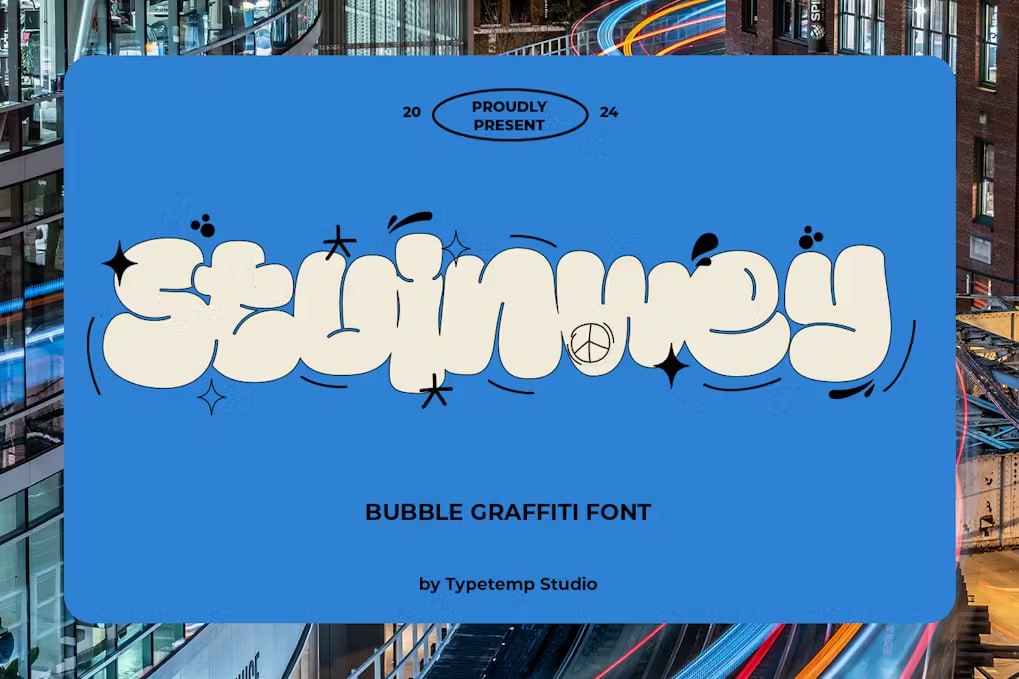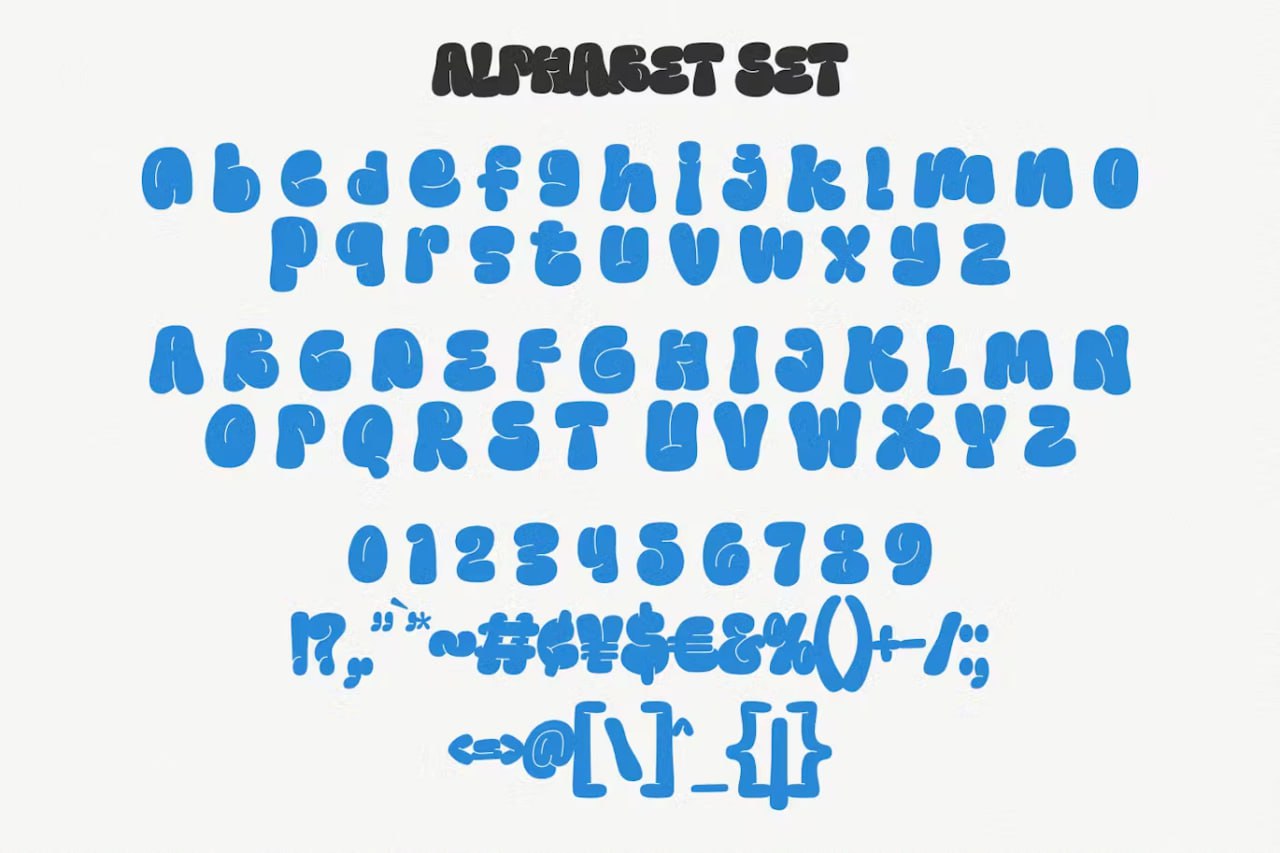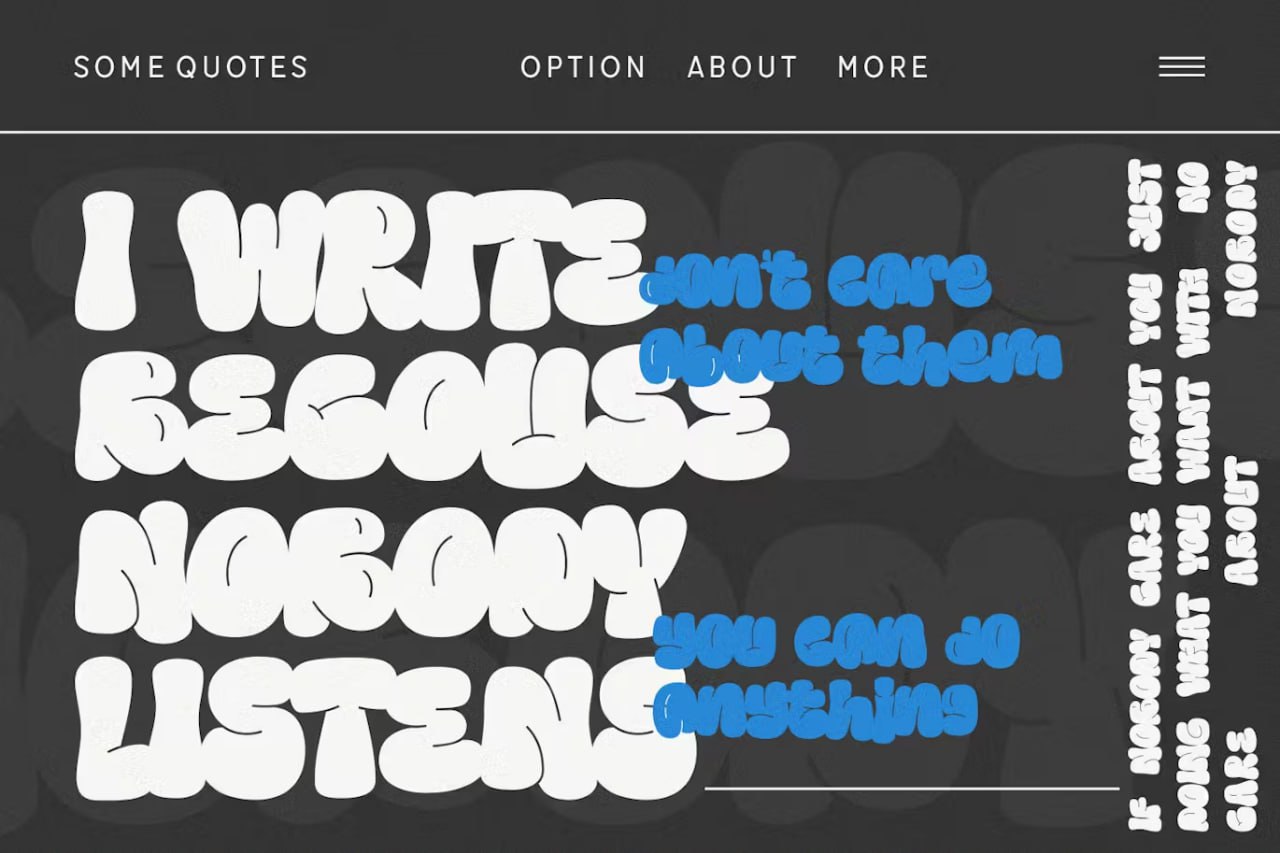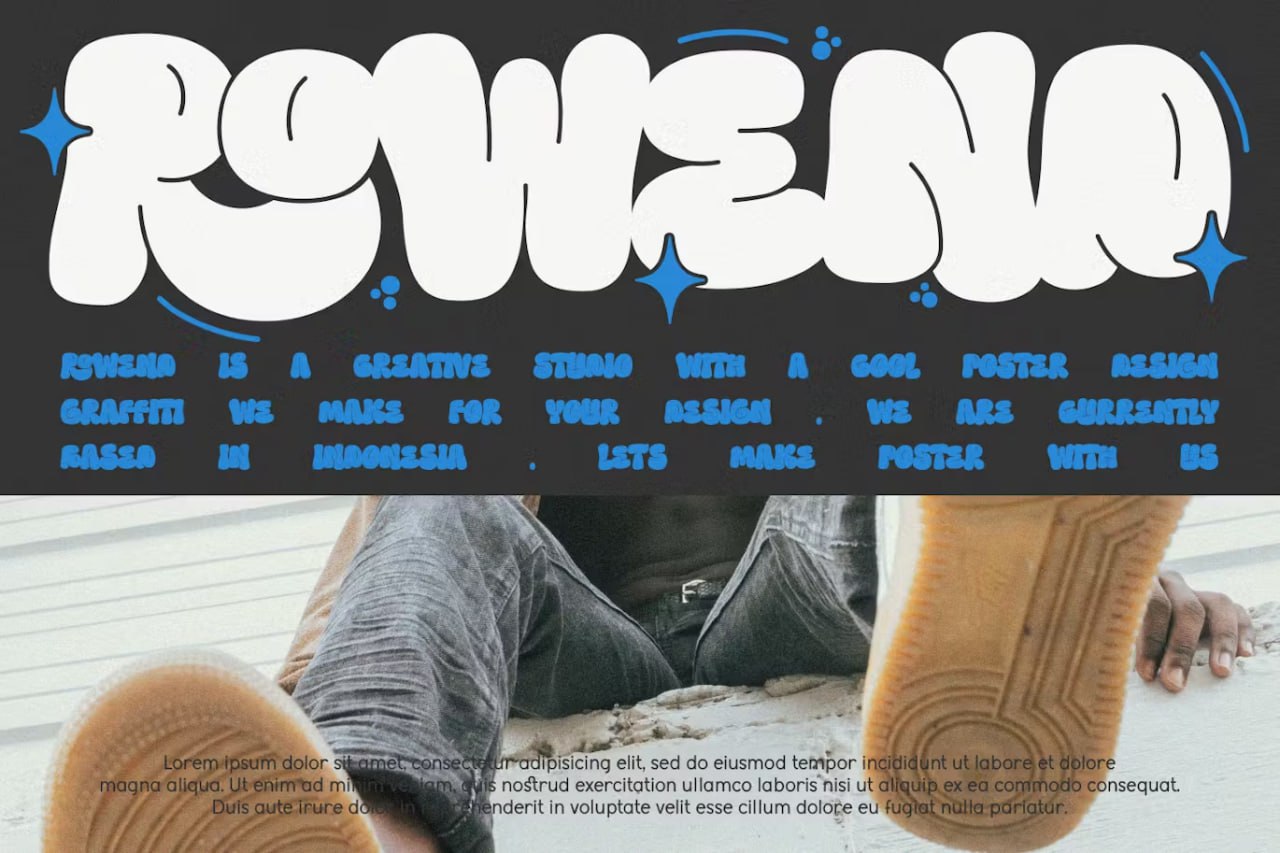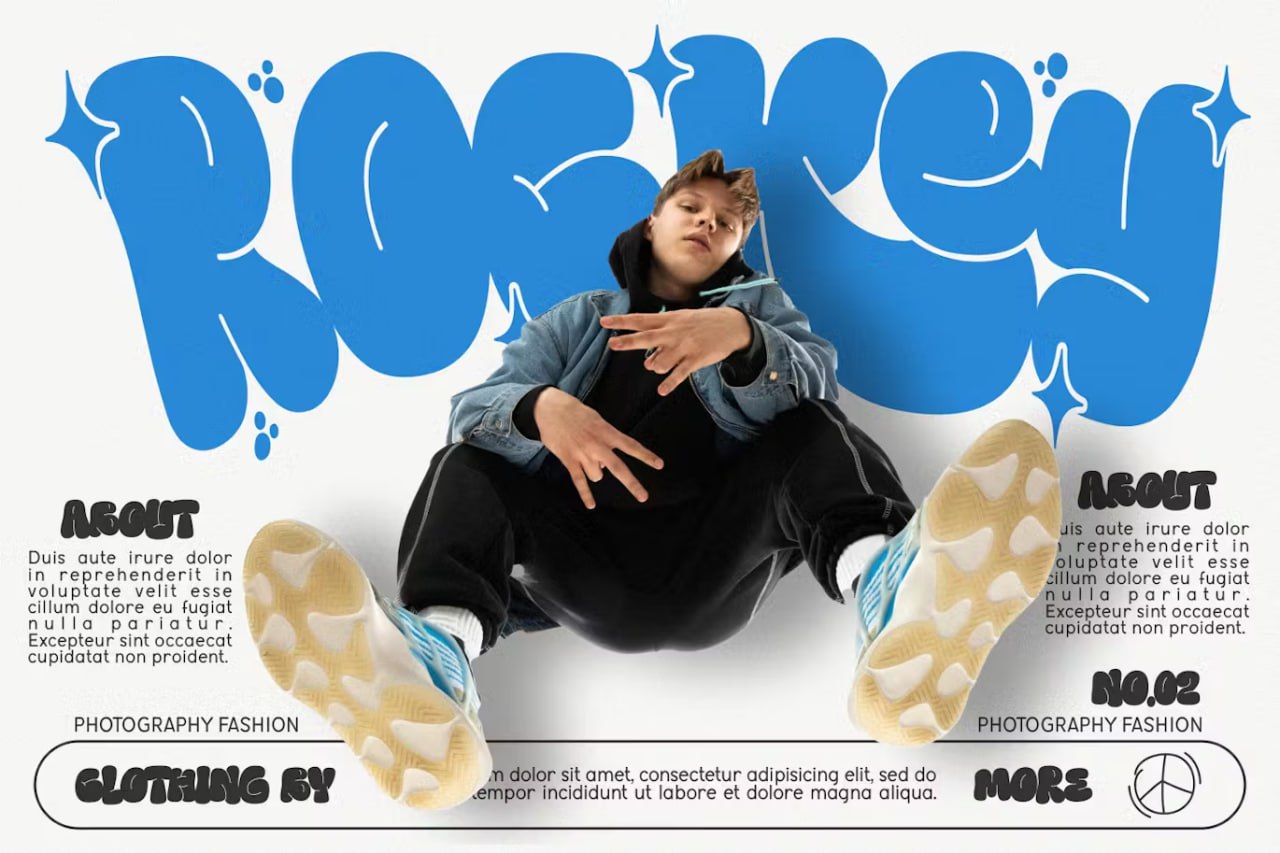
Entre modernité, élégance et vibes 80s/90s, Stuinwey est une police d'affichage au style unique, mêlant influences classiques, modernes et rétro. Parfaite pour sublimer vos logos, citations, posts, projets branding, magazines, invitations et plus encore.
• Formes de lettres originales avec alternatives & ligatures
• Identité visuelle
• Éditorial & affichage
• Mariages & papeterie de luxe
• Réseaux sociaux & contenus créatifs